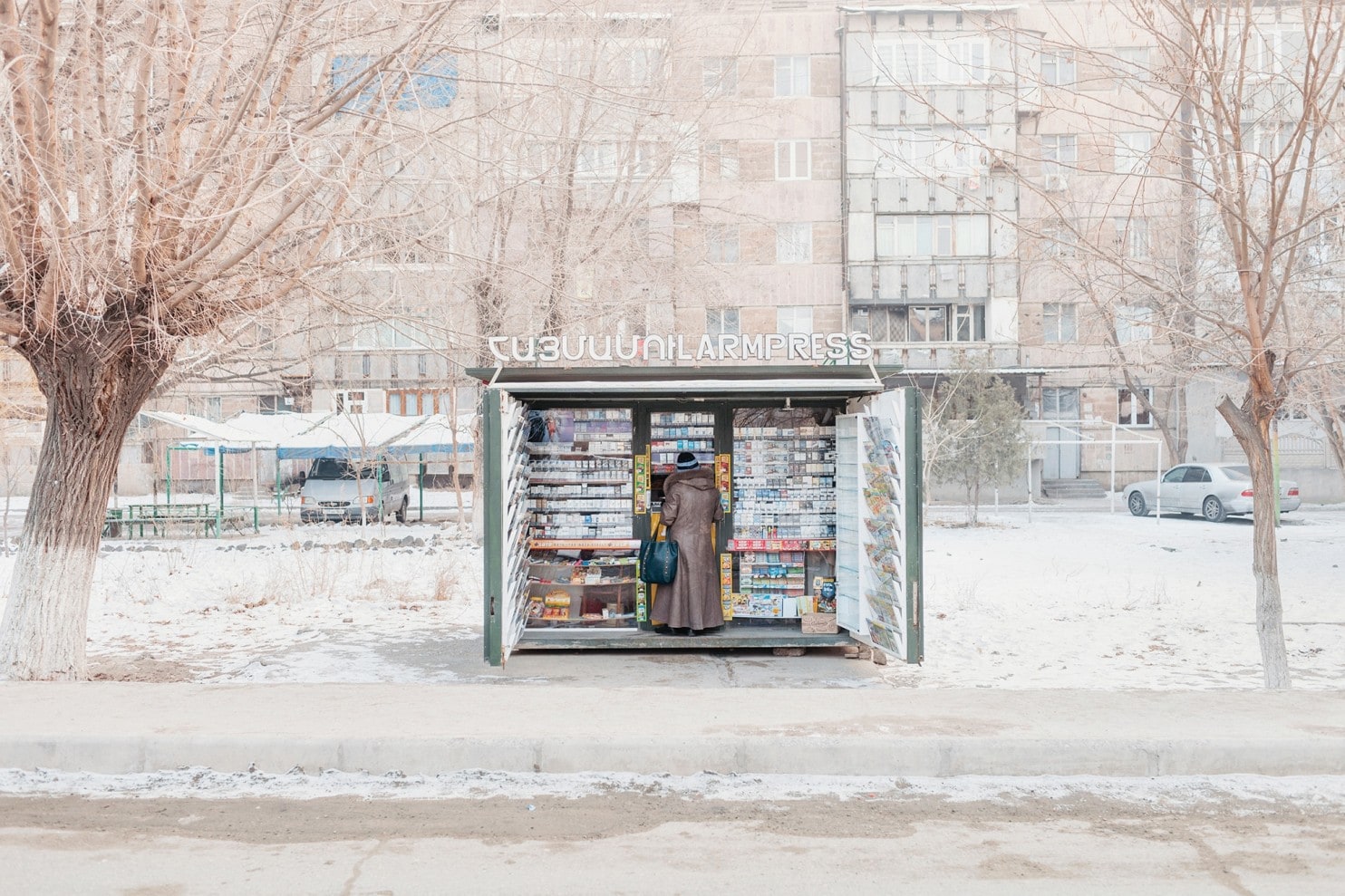
Eine (für meine naives Auge) sehr schön minimalistische und gut mit dem Lateinischen harmonierende Interpretation des Armenischen Alphabets:
Entdeckt in der Washington Post. Nochmal näher ran: